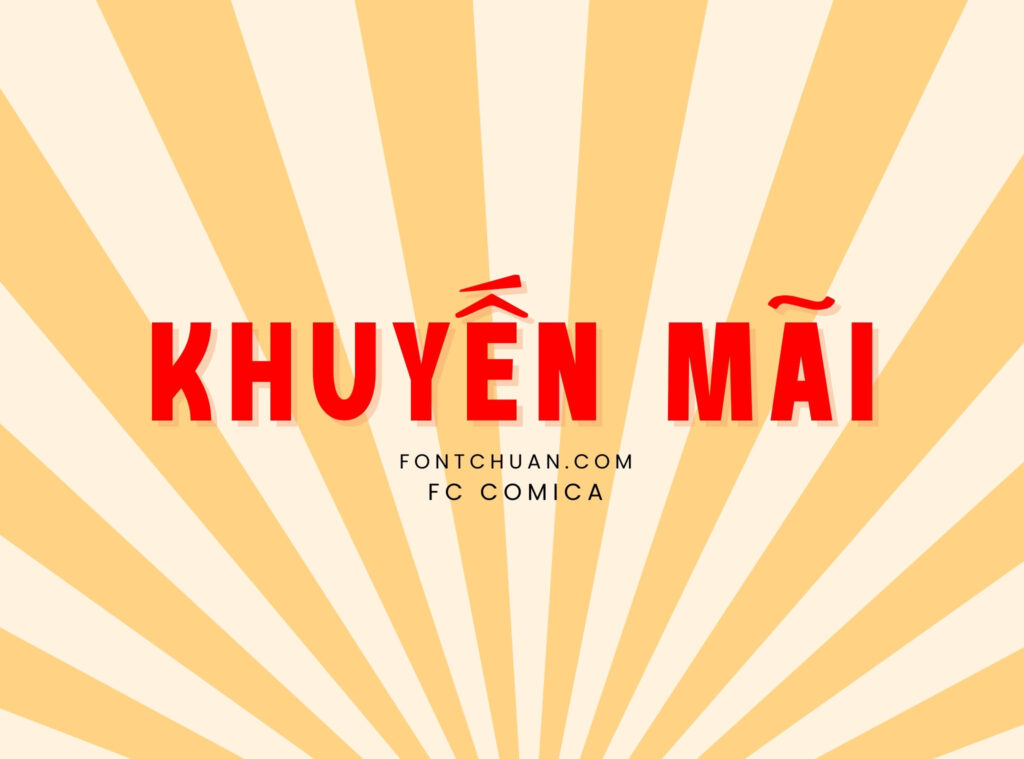
Comica là một kiểu chữ sans serif được thiết kế bởi Roiyani Teungku và phát hành bởi Groen Studio. Font này được lấy cảm hứng từ phong cách chữ viết tay trong các truyện tranh, mang lại cảm giác thân thiện và vui tươi. Comica hỗ trợ đa ngôn ngữ, bao gồm cả tiếng Việt, giúp các nhà thiết kế tiếp cận đối tượng người dùng rộng rãi.
Về thiết kế, Comica sở hữu các đường nét gọn gàng, cấu trúc chữ cân đối và đa dạng về trọng lượng, phù hợp cho nhiều mục đích sử dụng như thiết kế logo, tiêu đề, poster, bao bì sản phẩm và các ấn phẩm quảng cáo khác.